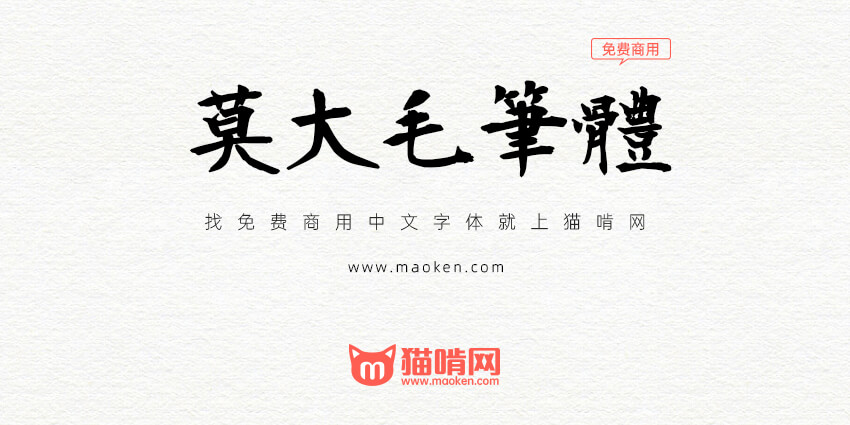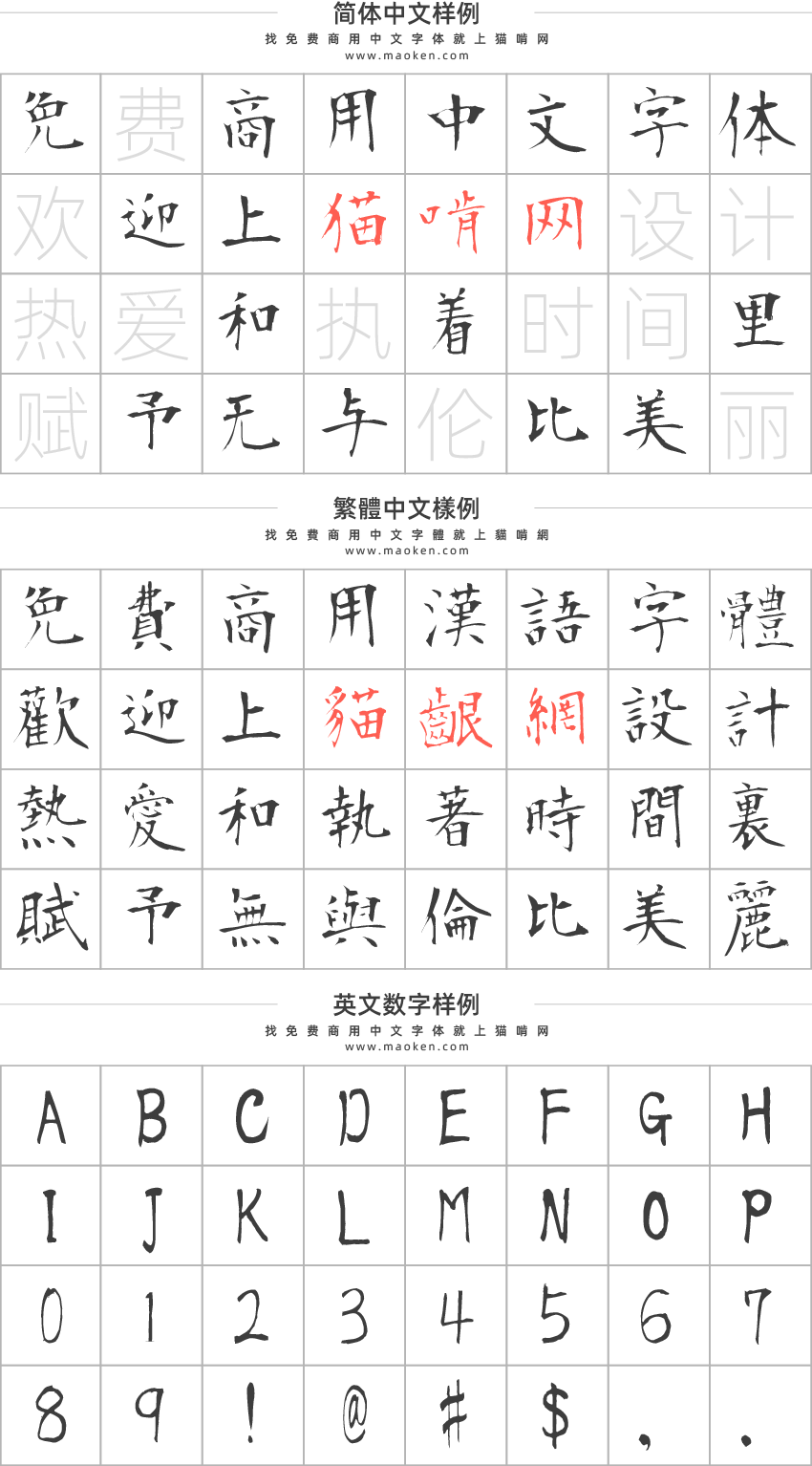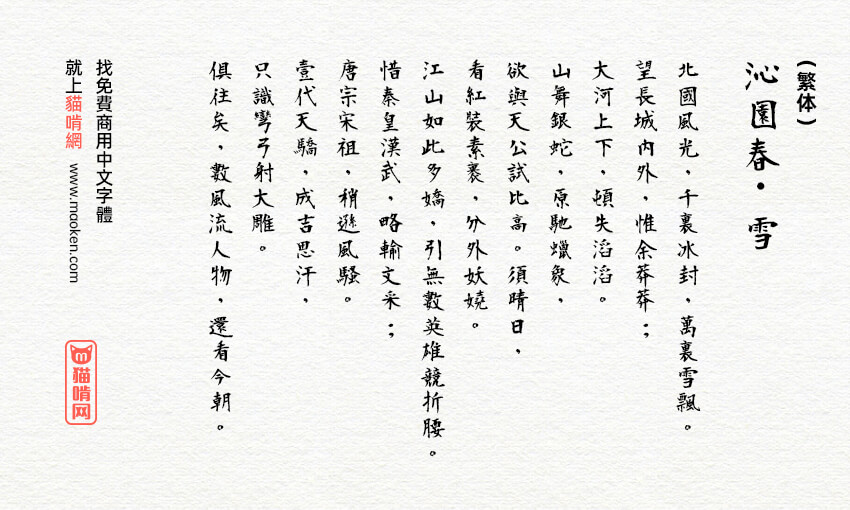
字体名称:莫大毛筆 | 字体版本:Version 1.35 2020.03.07 |
字体作者:Max(中国台湾) | 字体字重:4个 |
莫大毛笔体是基于衡山毛笔体的开放原始码中文字型增加更多字重的字数的修改版字体。衡山毛笔字体是来自于日本书法家青柳衡山,目前字型内文字和符号字数在:14,321个。
与衡山毛笔体体有何不同?
1、增加了更多中文字体
莫大毛笔体补齐台湾教育部列出的4,808个常用字,在原本的衡山毛笔字体架构下,莫大毛笔字体增加(和修改)168个字。
2、增加了字体字重,现在总共5个字重
原本的衡山毛笔字体放在Regular字重裡,现在透过程序自动产生ExtraLight、Light、Medium、Bold 新的字重。Light字重是把原本的KouzanBrushFont微微调细一点点。在ExtraLight的字重裡,可能会因为笔划太细造成某些笔画消失。在Medium和Bold的字重裡,可能会因为笔划太粗造成某些笔画重叠难以识别,有粗体字的需求,可以先挑战使用Bold字重看看,如果发现效果不如预期,再改用Medium字重。
不能确定自动产生出来的字重裡每一个都是完整的字,毕尽程式会误判是常有的事情,所以不是在Regular字重裡的笔划可能会消失。
3、清除衡山毛笔字体裡空白的文字
衡山毛笔字体裡有很多空白的字, 会造成无法让系统自动用预设字体来补字,已清除空白的文字。
4、调整标点符号位置
衡山毛笔字体的全形标点符号针对日本做设计,调整为台湾常见的置中用法。半形的backslash,调整为非日本地区用法。
5、增加部分台湾口语出现的中文字和增加部份的粤语字
在原本的衡山毛笔字体架构下,莫大毛笔字体增加11字。感谢网友Luke Liu的贡献,在莫大毛笔字增加86个粤语字。